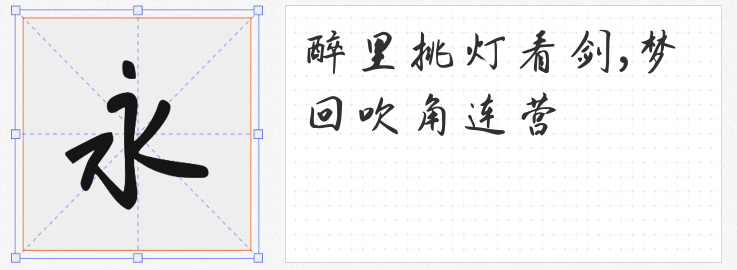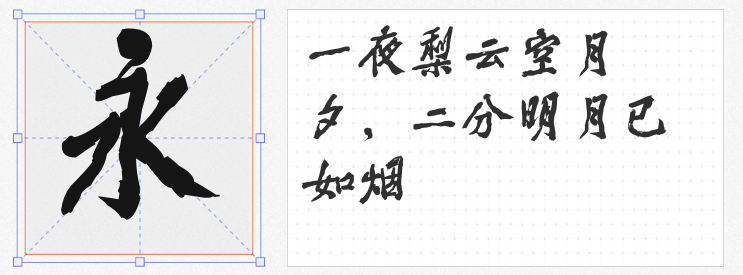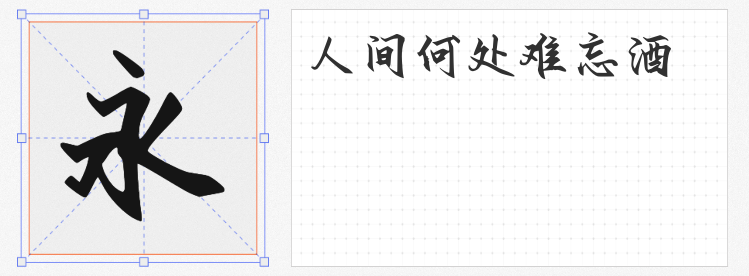
在商业设计中,手写与书法字体是传递品牌温度、增强视觉感染力的利器。本文精选四款风格各异且可免费商用的优质字体,助您轻松打造兼具文化底蕴与现代美感的作品。
1. 余思源颜黄体
这款字体以颜真卿的筋骨厚重为基底,融入黄庭坚"长枪大戟"的洒脱笔意,形成方圆结合的独特韵味。其笔画外拓舒展,横画如千里阵云,飞白处理克制而灵动,既规避了江湖体的浮夸,又保留了毛笔书写的自然肌理。作为同时支持简繁中文及多语种符号的完整字库,余思源颜黄体在包装设计、文化海报等领域能瞬间提升格调,在商务文件标题中亦显庄重大气。
2. 鼎猎西大体
以母校情怀为灵感源泉,这款手写行楷刻意保留了书写时的微小瑕疵,将校园岁月的青涩与真挚凝练成独特的排版韵律。其字形大小错落、笔画收放自如,特别适合美食菜单、文创产品等需要营造松弛氛围的场景。当用于艺术展览标题时,那种不事雕琢的随性之美,往往能引发观者共鸣。
3. 昆明海鸥体
设计师耗时两月,将红嘴鸥的飞翔姿态转化为汉字结构,创造出这款兼具碑帖古韵与生态趣味的创新字体。其字形修长却不失稳重,笔画转折处暗含海鸥振翅的动态弧线,在旅游宣传、儿童读物等领域极具辨识度。作为国内首款动物主题书法字体,昆明海鸥体为品牌注入难得的在地文化基因。
4. 黄凯桦律师手写体
由AI神笔造字技术生成的这款字体,完美复现了律师职业特有的理性克制与人文温度。其字形工整中带轻微连笔,既保持专业文件的易读性,又通过笔触起伏传递书写者的个性印记。在法律文书、企业报告等场景应用时,能有效软化严肃文本的疏离感。